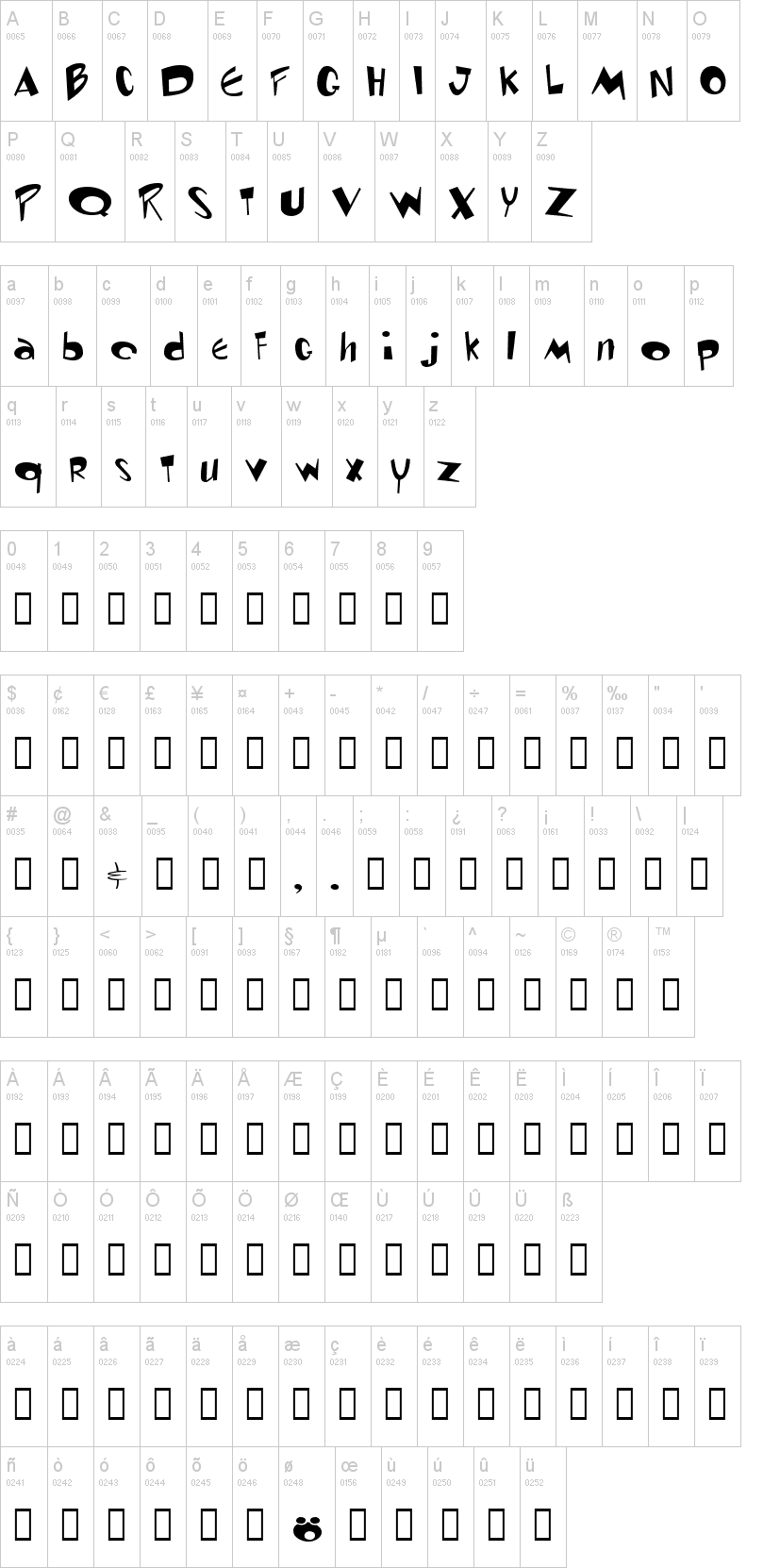
Toontime是由设计师Sandy Drobic和James Grieshaber在1999年创造的一种字体。这是一种游戏和动画风格的字体,非常适合于儿童书籍、漫画、动画、电影、广告、海报等方面的应用。 Toontime字体的字母基本上是圆形和弯曲的,看起来非常有趣和可爱。它的每个字母都有一个独特的动画感觉,似乎在跳动和跳跃,这使得它非常适合于那些需要引起读者注意力和兴趣的项目。 除此之外,Toontime字体还有一些特殊的符号和标点符号。例如,它包括许多带有笑脸或表情符号的符号,这使得它非常适合用于儿童相关的设计项目。 总体来说,Toontime字体是一种非常有趣和引人注目的字体,非常适合用于儿童和动画相关的设计项目。内容介绍
Toontime是一款非常不错的手写艺术字体,具有很好的视觉感,适合于文化类的宣传设计、商业类品牌的广告和产品包装设计以及个性化文字排版等较多场景。